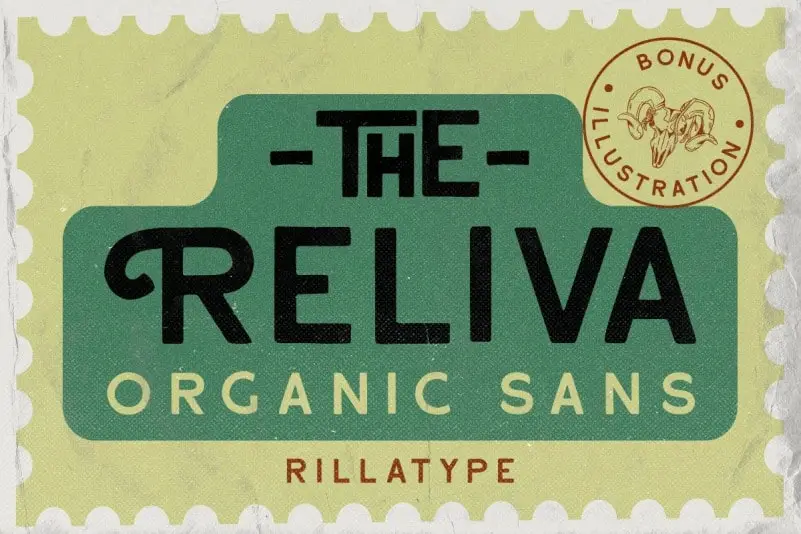
Reliva Sans Serif Font – Download Grátis
A Reliva Sans Serif Font é uma elegante tipografia de letra aberta que transborda leveza e fluidez. Inspirada na escrita manual, esta tipografia oferece muitas alternativas e ligaturas para garantir sua singularidade. O design vem com seis ilustrações de alta qualidade, adicionando um toque único aos seus projetos criativos. Experimente a Reliva na criação dos seus logotipos, marcas, embalagens e citações — você notará como ela dá vida ao seu trabalho! A Reliva é a fonte perfeita para transformar suas ideias em realidade visuais memoráveis.